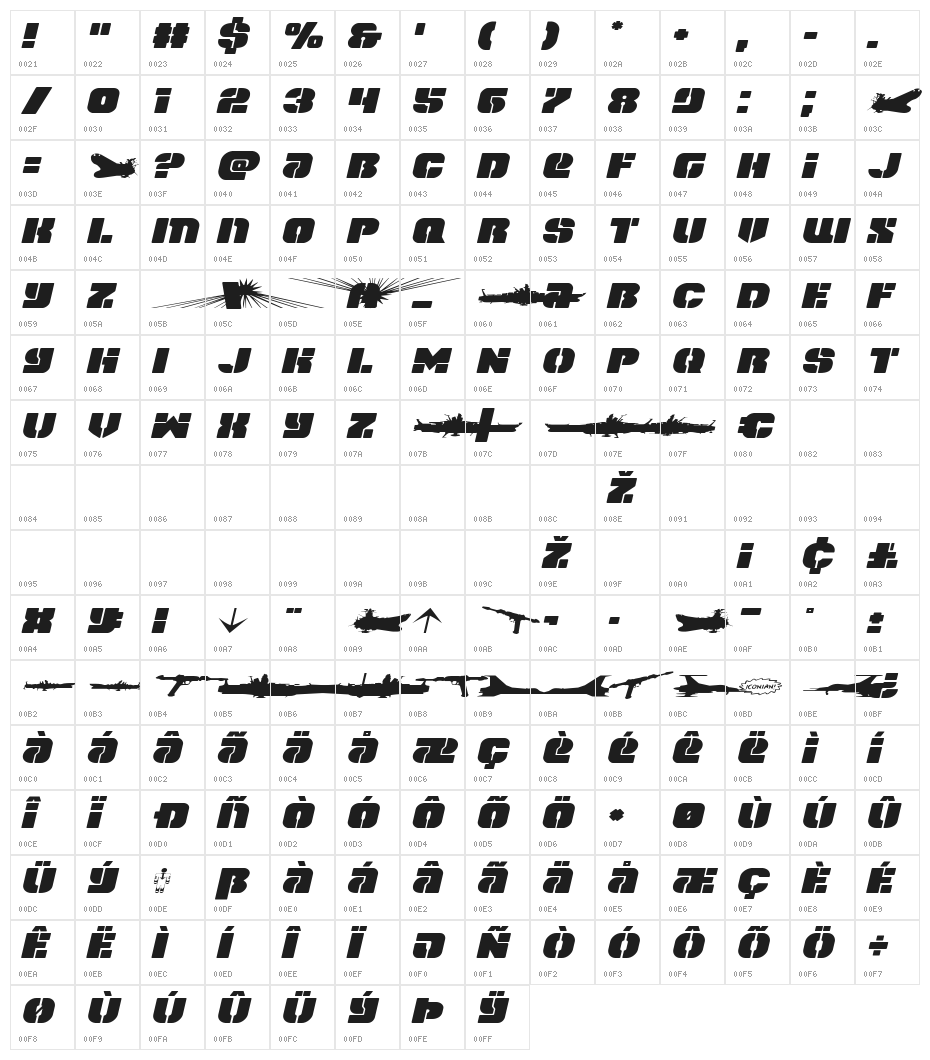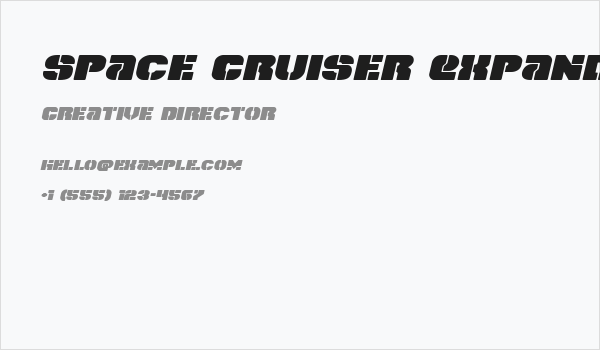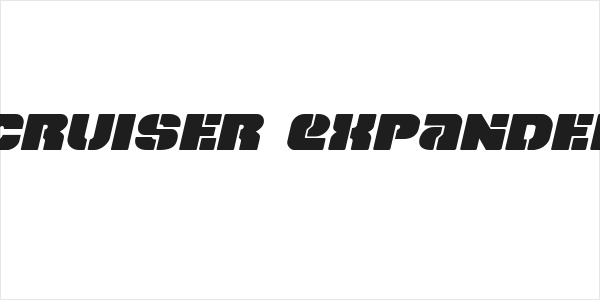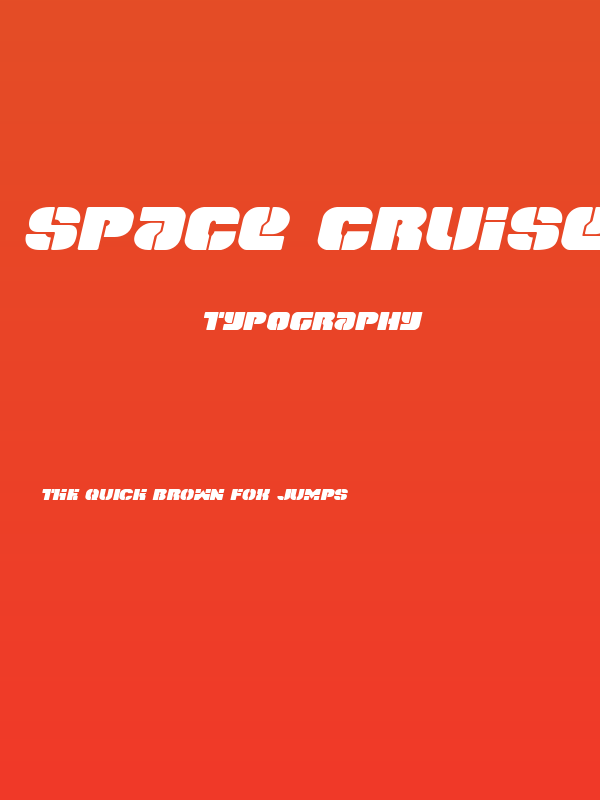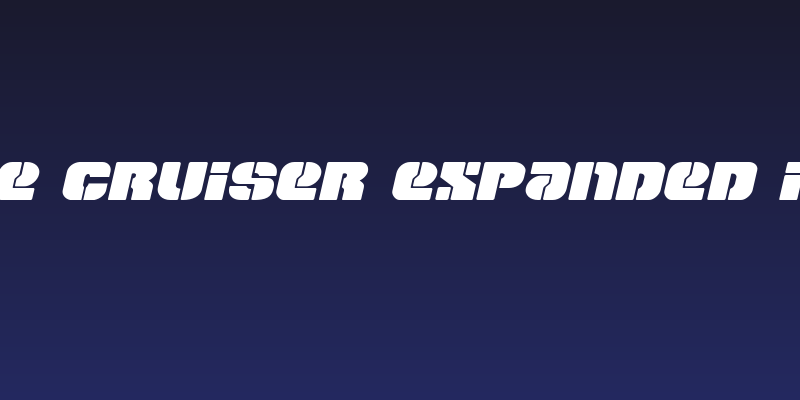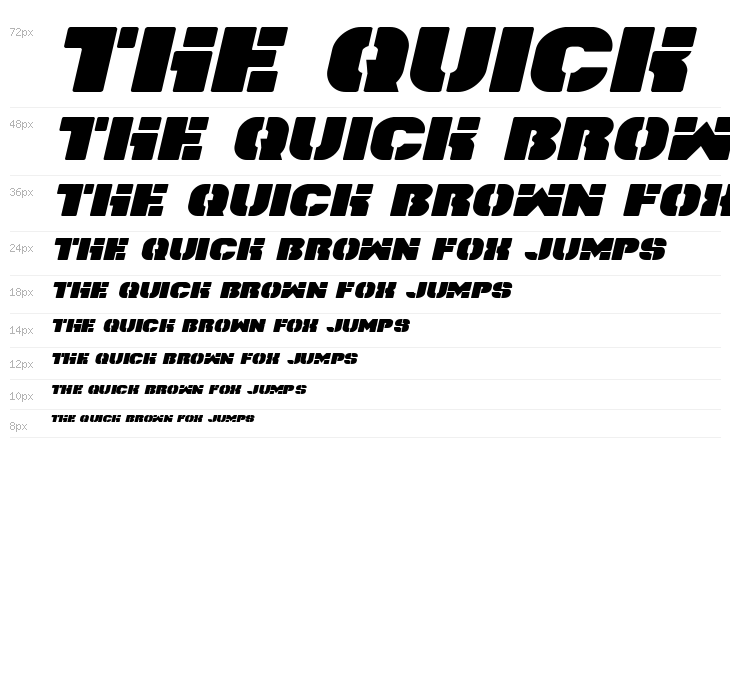
Space Cruiser Expanded Italic Font
| Progetti proposti | Ideal for sci-fi themed posters, video game titles, futuristic branding, and technology-related advertisements. |